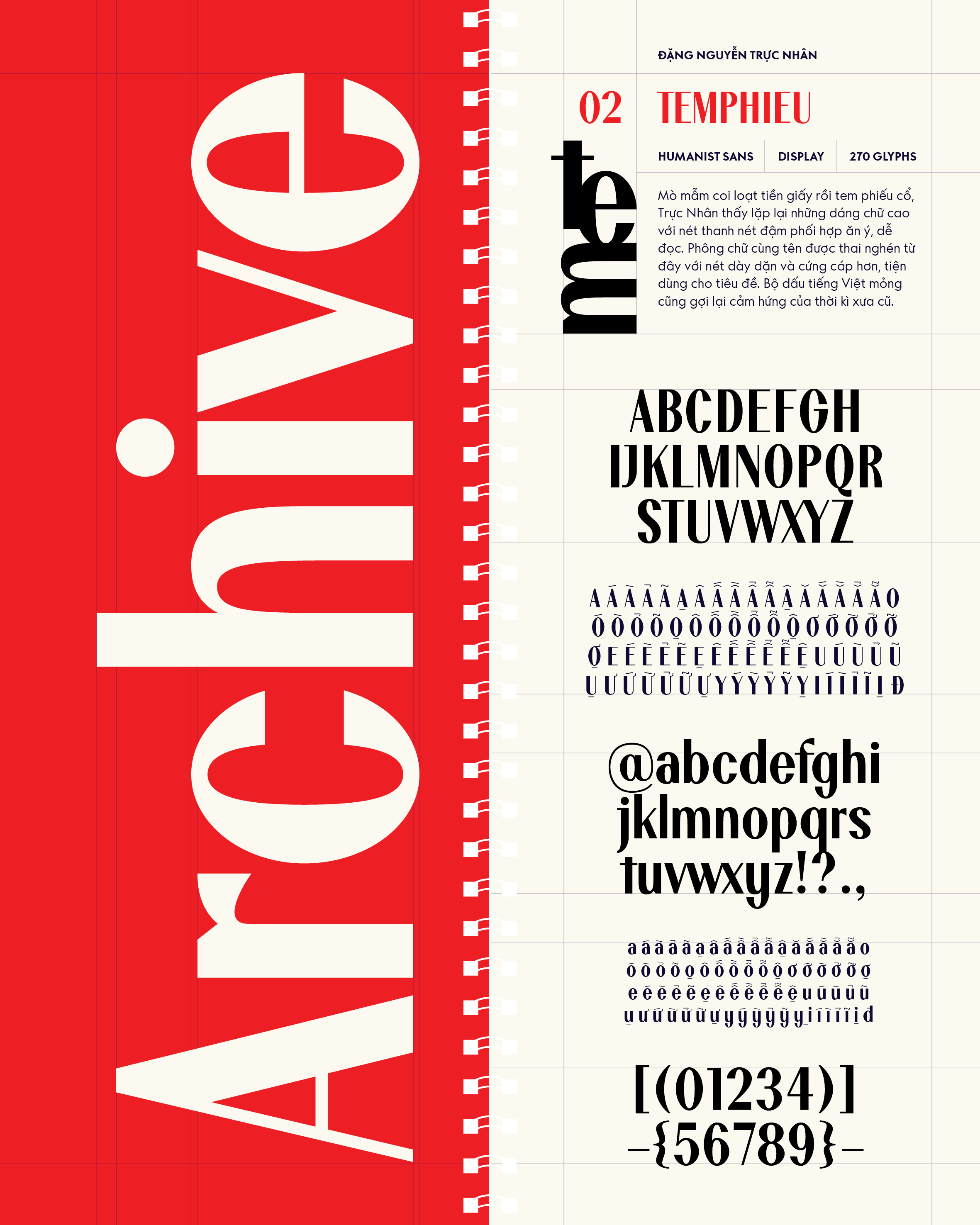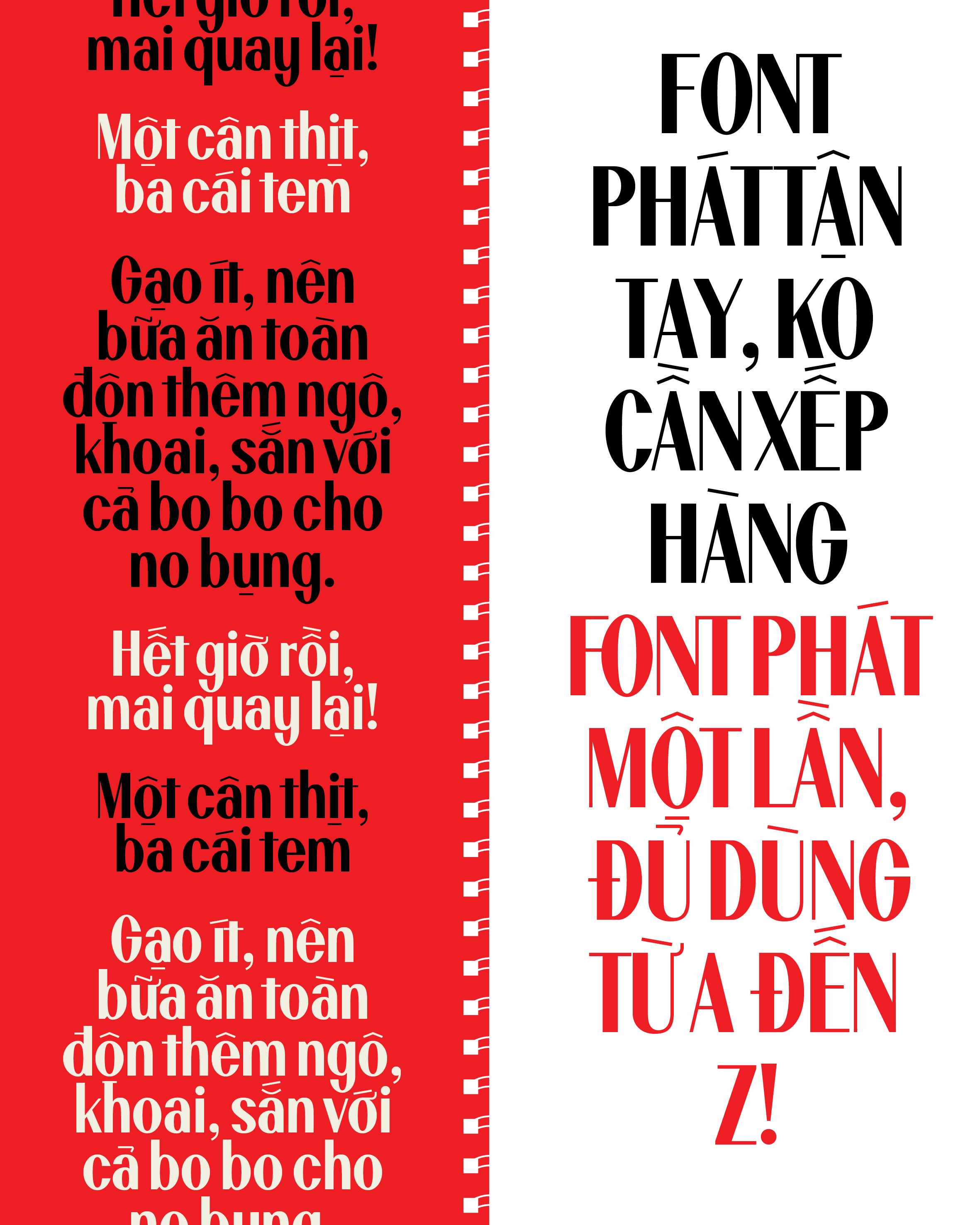
Temphieu
Về Temphieu: Mò mẫm coi loạt tiền giấy rồi tem phiếu cổ, Trực Nhân thấy lặp lại những dáng chữ cao với nét thanh nét đậm phối hợp ăn ý, dễ đọc. Phông chữ cùng tên được thai nghén từ đây với nét dày dặn và cứng cáp hơn, tiện dùng cho tiêu đề. Bộ dấu tiếng Việt mỏng cũng gợi lại cảm hứng của thời kì xưa cũ.
Humanist Sans-serif
Display
Trực Nhân